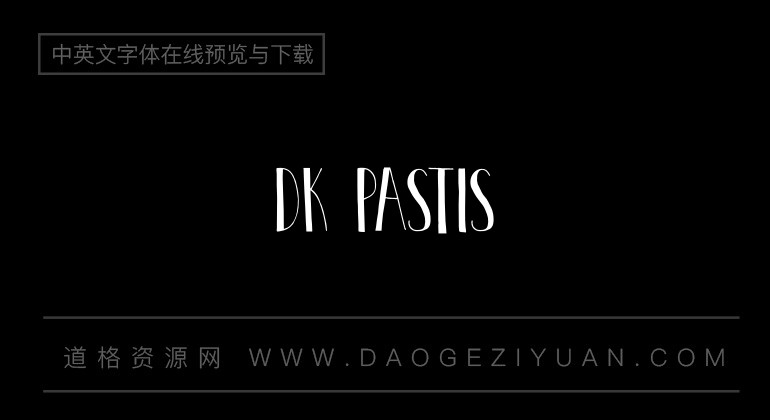
DK Pastis
DK Pastis 是一种优美的手写字体,它由 David Kerkhoff 设计,具有流畅的圆弧和精心设计的笔画。这种字体的特点是它的线条自然、优雅,类似于书法的感觉,同时也不失清晰易读。它的笔画比较细,适合用于书籍、文献、网站等场合的正文或标题字体。此外,DK Pastis 还配备了多种特殊字符和符号,适用于多种语言,如英语、法语、西班牙语和德语等。如果您正在寻找一种漂亮、易读的手写字体,那么 DK Pastis 可能是您的不二选择。
DK Pastis是一款非常不错的手写艺术字体,具有很好的视觉感,适合于文化类的宣传设计、商业类品牌的广告和产品包装设计以及个性化文字排版等较多场景。